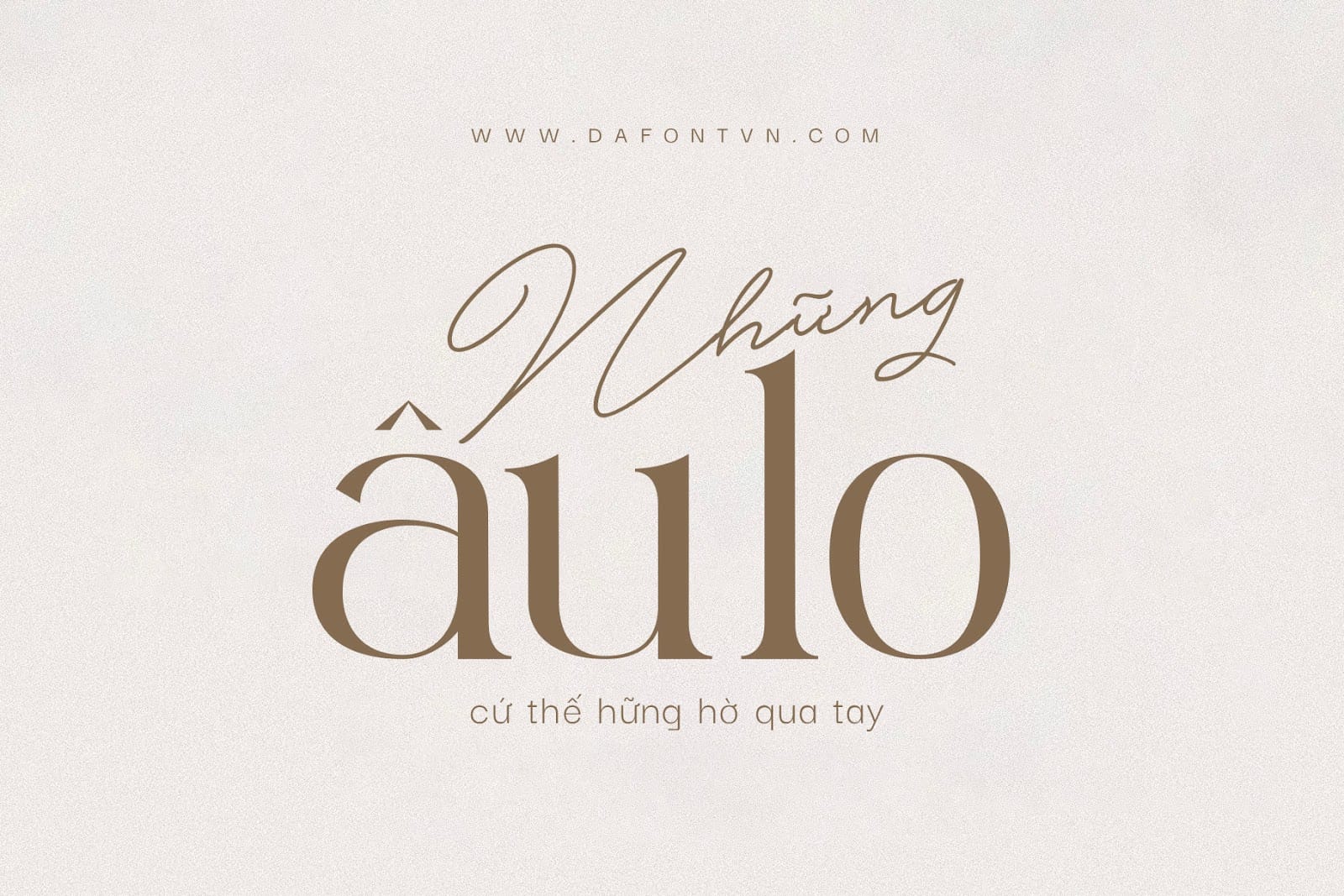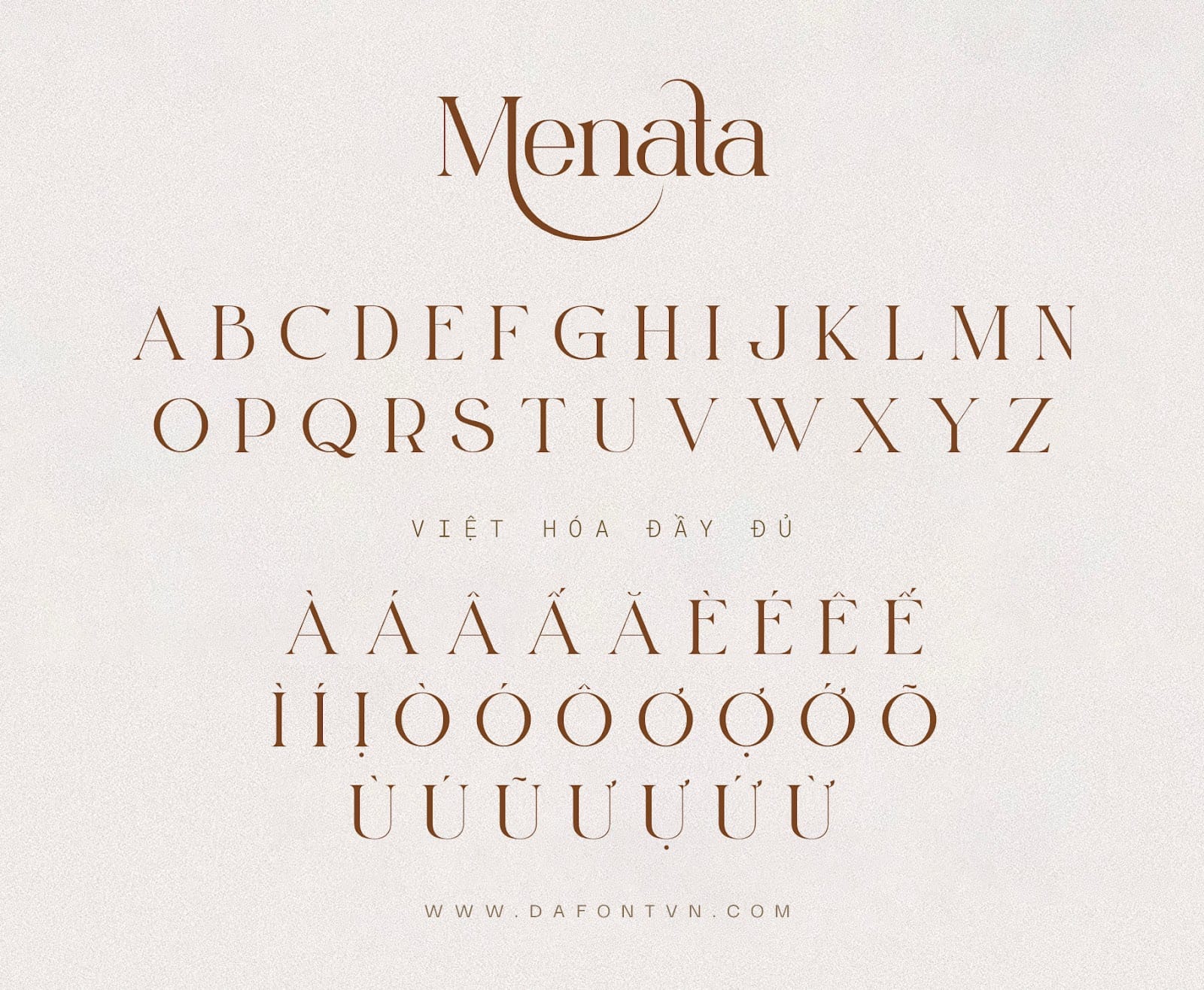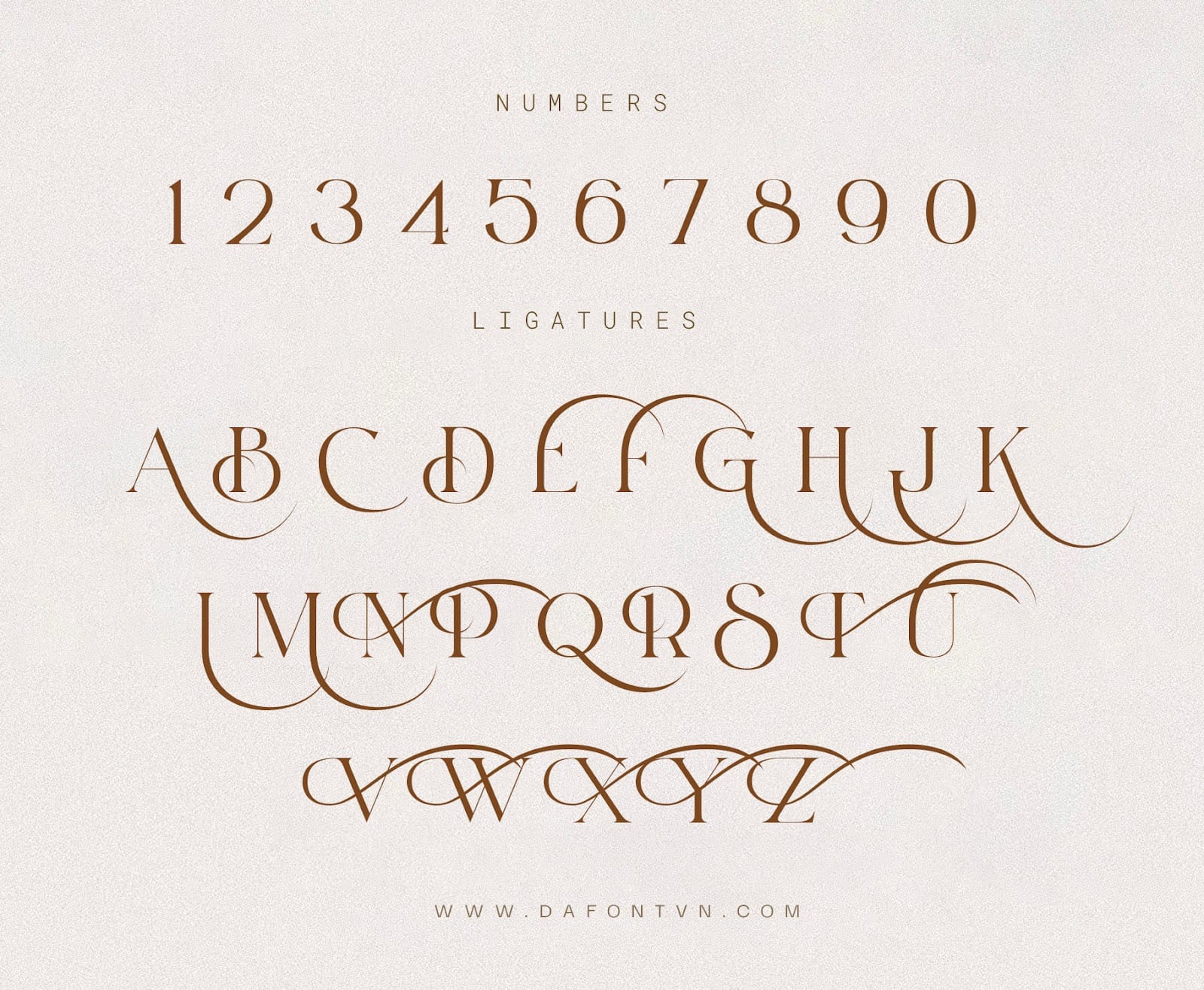
Menata – Serif classic Modern là một kiểu Serif cổ điển và hiện đại được hỗ trợ bởi các lựa chọn thay thế đặc biệt và việt hóa hoàn chỉnh, có tới 170 lựa chọn thay thế thú vị làm cho phông chữ này linh hoạt và hoạt động tốt ở nhiều kích cỡ khác nhau. Các glyph thay thế với các đường nét được thiết kế uốn lượn mang một điểm nhấn đặc biệt cho font.Font được việt hóa đầy đủ, kerning và feature lại để phù hợp với các dấu tiếng Việt ngoài ra font mã hóa PUA để sử dụng trên nhiều các phần mềm thiết kế khác nhau. Phông chữ này hoàn hảo cho nhiều thiết kế khác nhau như logo, thương hiệu, thiệp mời, tạp chí, nhãn hàng, sản phẩm… Vì các đường nét hơi mảnh do đó phông này phù hợp cho các tiêu đề lớn.